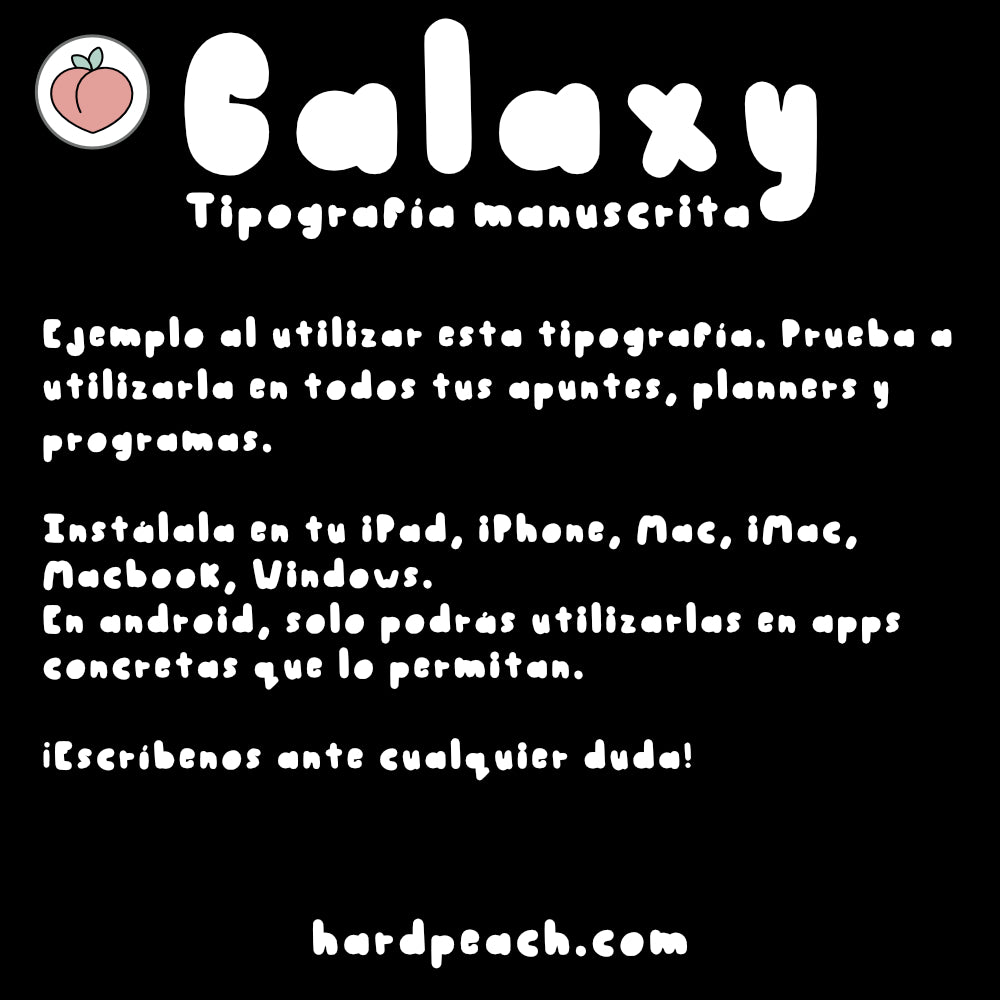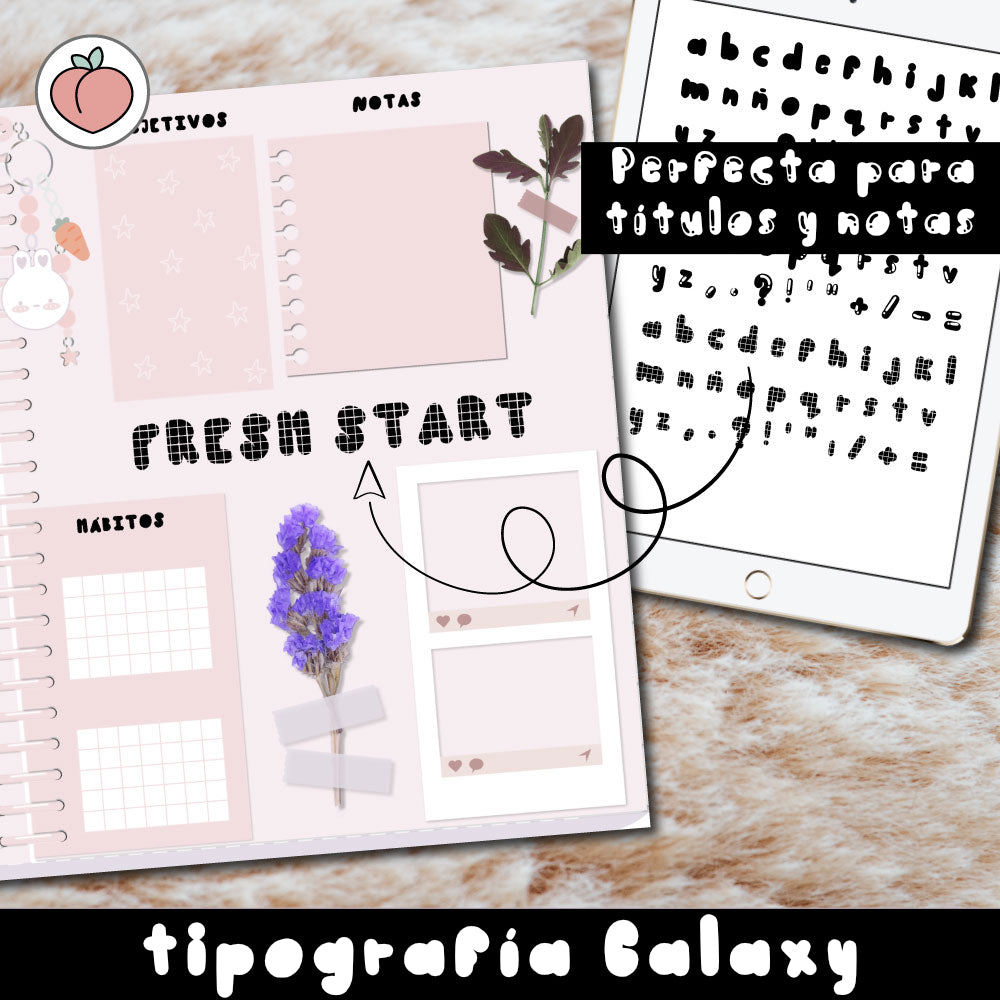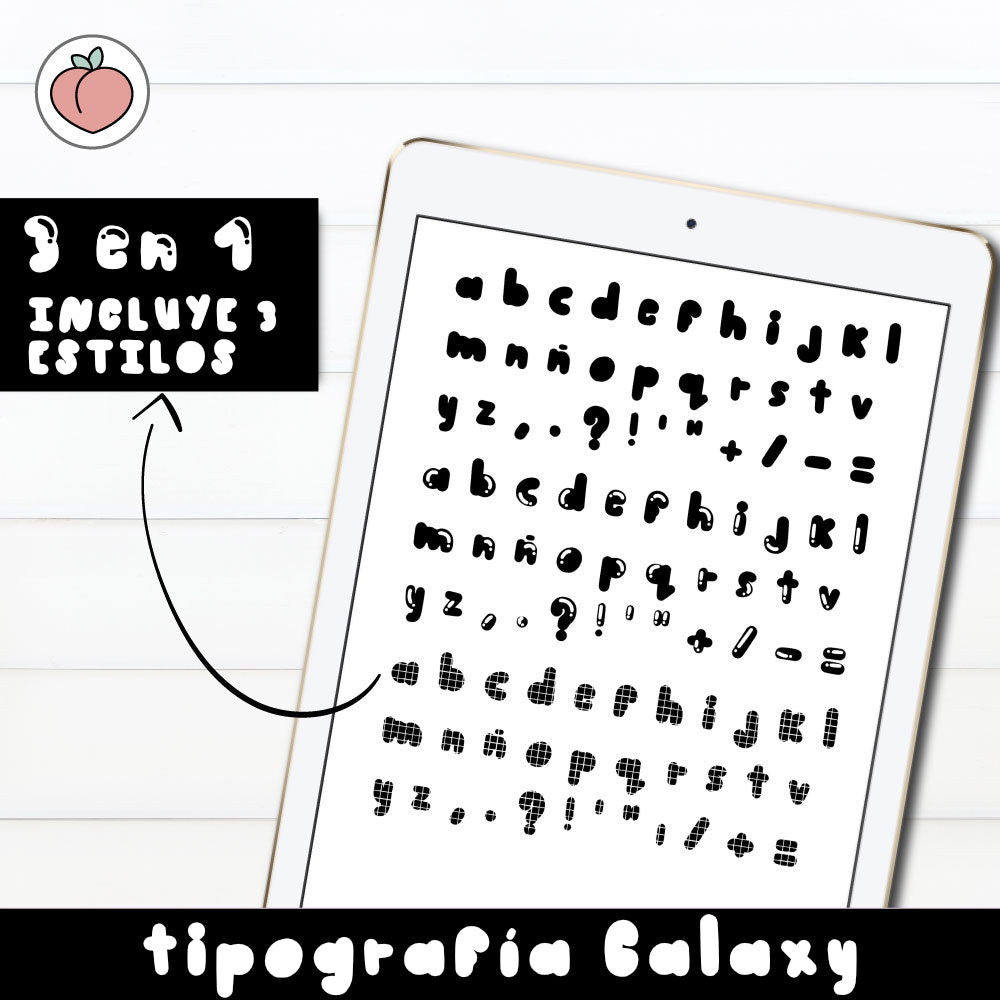
TIPOGRAFÍA GALAXY | ESTILO REDONDEADO PARA TÍTULOS, ENCABEZADOS, BULLET JOURNAL...
La tipografía Galaxy es una fuente redondeada, amigable y moderna, perfecta para darle un toque único y divertido a tus apuntes, notas, esquemas, bullet journals, agendas, títulos o cualquier proyecto creativo.
Incluye el alfabeto español completo, con mayúsculas, minúsculas, números, acentos y símbolos principales, lo que la hace ideal para todo tipo de escritura académica, profesional o creativa.
Galaxy es perfecta para estudiantes, creativos y profesionales que quieran que sus apuntes digitales, títulos, notas y proyectos luzcan originales y bien organizados, combinando estética y practicidad.
Dale a tus proyectos, bullet journals y apuntes un estilo redondeado, moderno y encantador con la tipografía Galaxy, y transforma cualquier texto en algo divertido, legible y con personalidad.
Esta tipografía está en Español incluye todos los caracteres principales, mayúsculas, minúsculas, números, vocales con tildes (español) y algunos signos esenciales. Al estar en Español, no incluye algunas acentuaciones de otros dialectos o idiomas.
Esta tipografía cuenta con los siguientes caracteres:
Abecedario de la A a la Z
Números del 0 al 9
Signos de puntuación más utilizados en Español
Signo de interrogación y exclamación
Versión en negrita
Versión cursiva
Genial para títulos y decoración
Hermoso